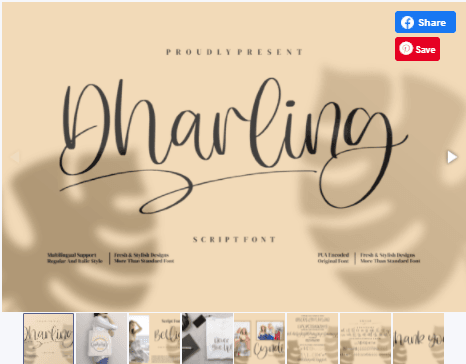
Dharling Font
Dharling - шикарный изысканный шрифт, излучающий изысканность и элегантность. Его стильные альтернативы и лигатуры делают этот шрифт идеальным для любого проекта. Dharling имеет кодировку PUA, что означает, что вы можете легко получить доступ ко всем глифам и росчеркам!